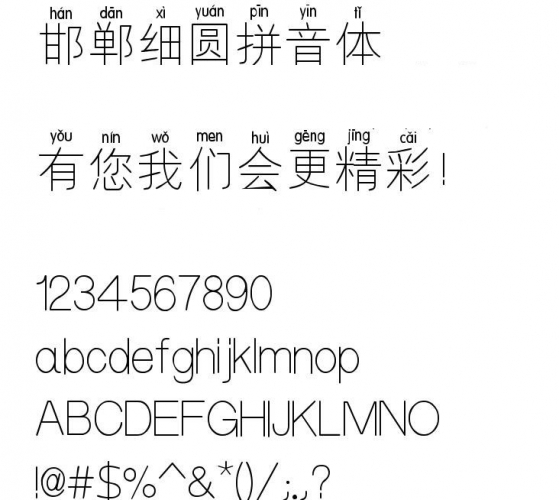
邯鄲細(xì)圓體拼音字體是邯鄲字庫(kù)中推出的一款細(xì)圓字體,字體端莊大方,單線超細(xì)的拼音體,能夠應(yīng)用于文本裝潢、信息展示、網(wǎng)頁(yè)設(shè)計(jì)、篆刻制模、數(shù)據(jù)制作、裝潢設(shè)計(jì)、計(jì)算藝術(shù)設(shè)計(jì)等多種領(lǐng)域,歡迎需要的朋友前來下載。